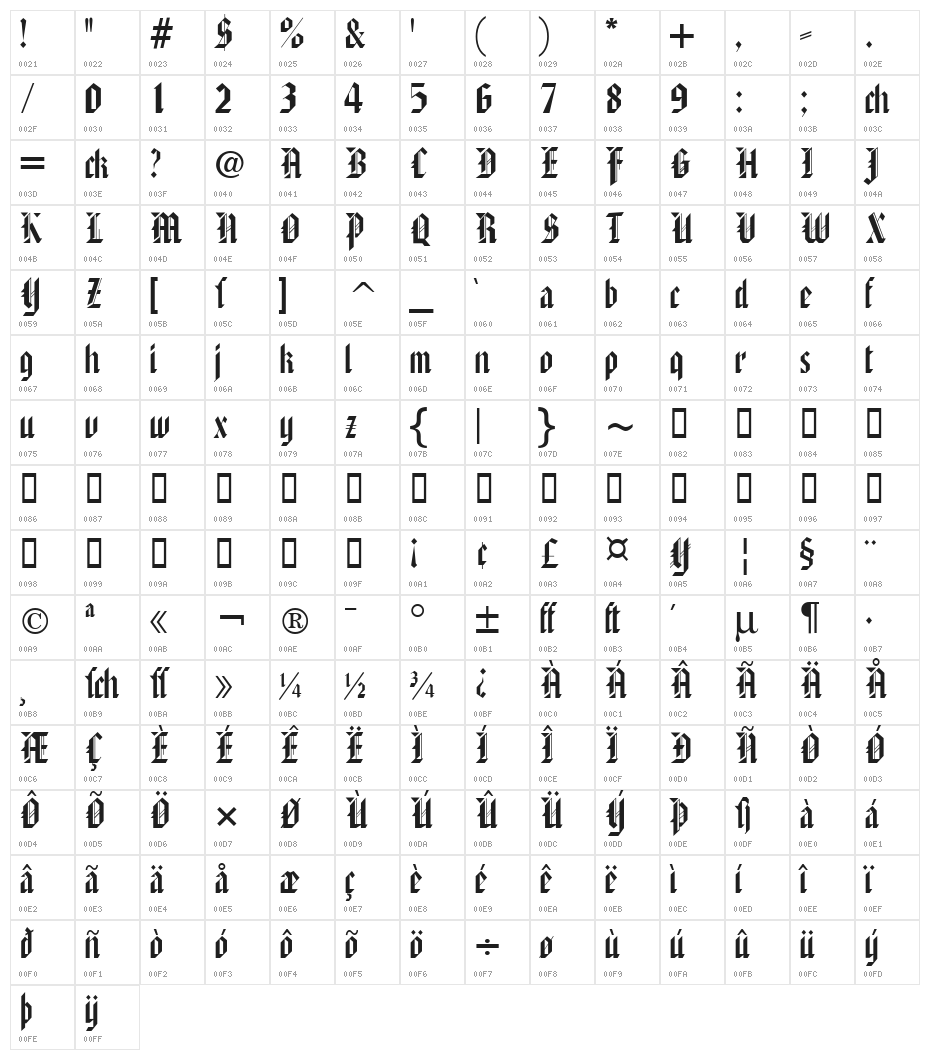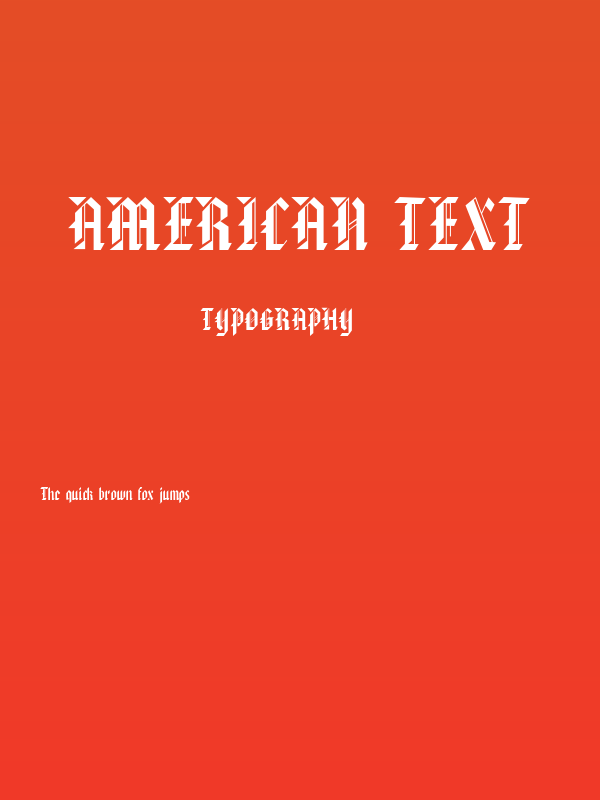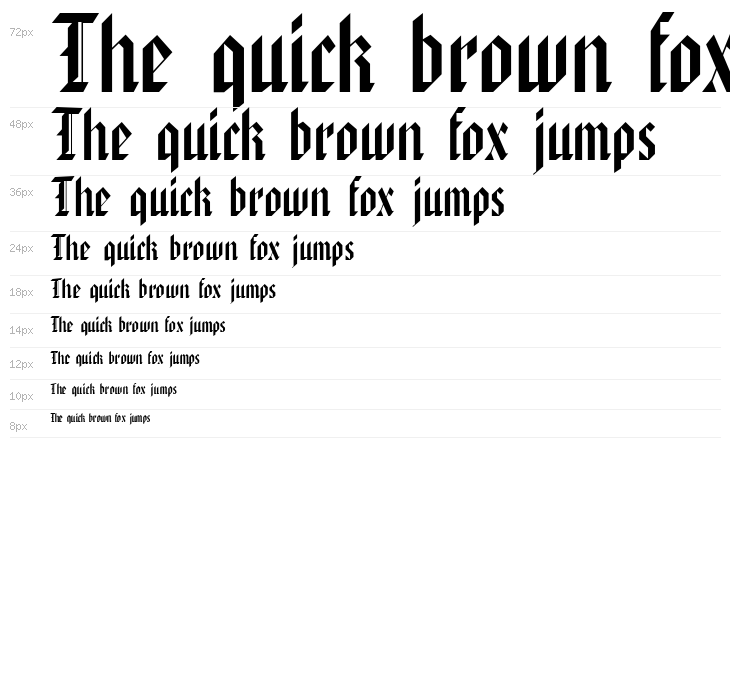
American Text Font
| Categorie | Gothic |
| Stile generale | Gothic, Historical |
| Caso d'uso | Headlines, Logos, Decorative |
| Progetti proposti | Ideal for posters, logos, branding materials, and any design requiring a historical or gothic aesthetic. |